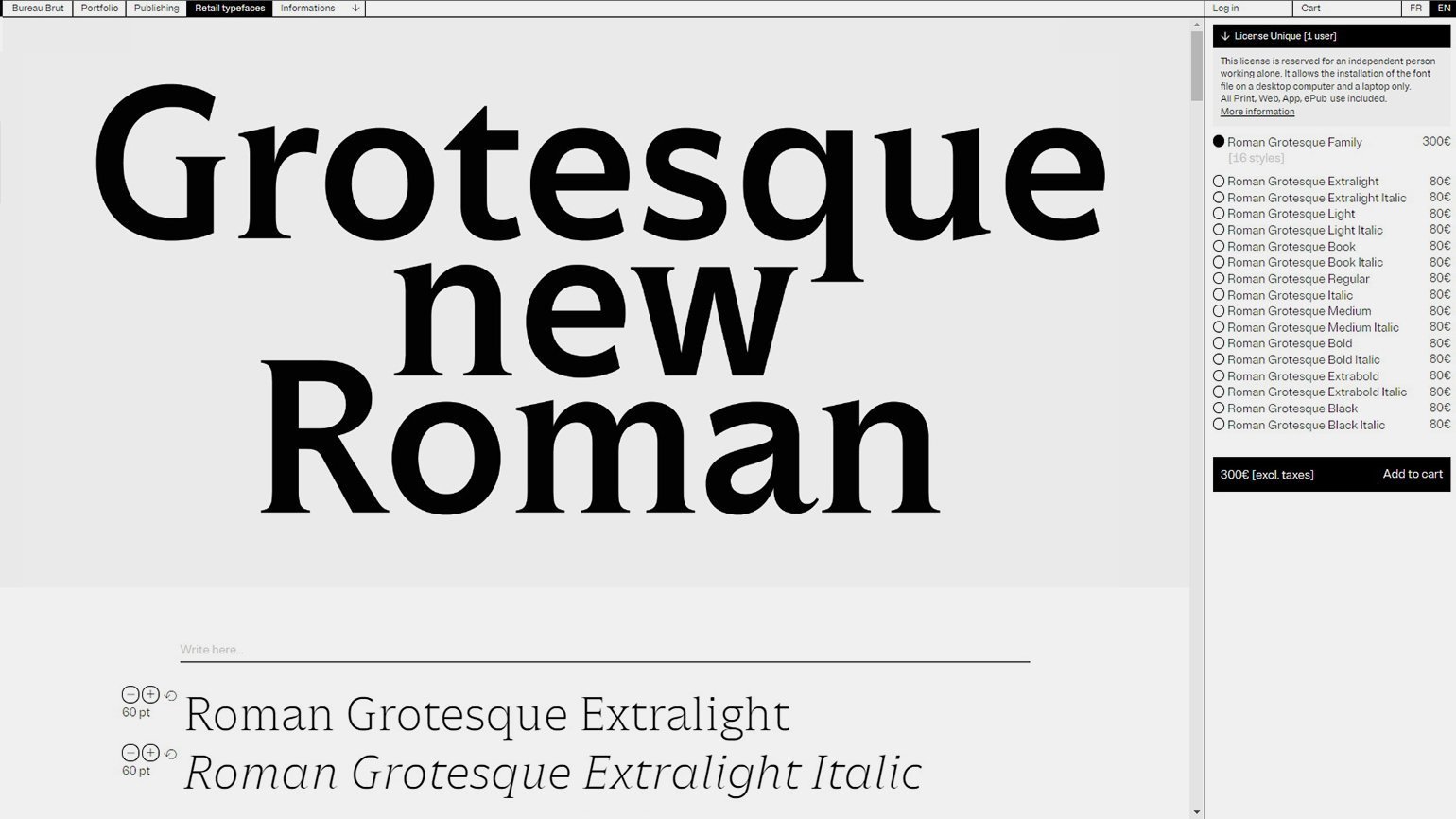
Неоднозначные термины: что такое брендбук, логотип и шрифт на самом деле
Надкусанное яблочко Apple — это не логотип, а заказчик просит сделать ему вовсе не брендбук. Рассказываем о путанице в терминологии.
Разночтения и неправильное использование терминов — проблема, которая встречается во многих сферах, и профессионального сленга графических дизайнеров она тоже касается.
Разберёмся, что на самом деле значат широко используемые термины и почему знать их настоящий смысл нужно, а вот правильно говорить — необязательно.
Брендбук и гайдлайн
Брендбук — это пособие для всех сотрудников, документ с изложением концепции бренда. В брендбуке описывают:
• философию компании;
• ценности корпоративной культуры;
• целевую аудиторию;
• конкурентные преимущества продуктов;
• а также — правила использования визуального фирменного стиля.
Для детального руководства по фирменному стилю есть отдельное название — гайдлайн.
В гайдлайне описание бренда и его мифов ограничивается несколькими абзацами, и эта информация в нём используется только для обоснования визуальных решений. А вот нюансы применения каждого элемента айдентики расписаны во всех подробностях.
Гайдлайн адресован не всем сотрудникам, а только маркетологам и дизайнерам, которые будут работать над рекламными кампаниями и поддержанием фирменного стиля компании.
Этот брендбук Skittles — инструмент бизнеса: он учит и вдохновляет сотрудников
Гайдлайн — это в первую очередь технический документ
Пример содержания гайдлайна: в нём прописаны используемые цвета, шрифты, допустимые версии фирменного знака, дизайн брендированной продукции
В обиходе и владельцы бизнеса, и дизайнеры зачастую называют гайдлайн брендбуком. Это привычно для всех, хотя формально неправильно.
Потребности в «настоящем», объёмном брендбуке у большинства компаний нет: «книги брендов» создают в крупных корпорациях с долгой историей и сложной системой маркетинга. А у небольших фирм характеристика бренда умещается в несколько предложений — и такого описания для гайдлайна достаточно.
Логотип и фирменный блок
Термин «логотип» образован от греческого «логос» — «слово». Правильное значение этого понятия — название компании, написанное именно буквами и определённым образом.
Слово martina — логотип, в котором шрифт сочетается со стилизованным изображением буквы «а»
Если же есть ещё и нарисованный символ бренда, эту картинку правильно называть фирменным знаком.
Изображение головы с лучами — фирменный знак, по которому бизнес можно узнать и без подписи
У Google, IKEA и многих других компаний нет рисунка-символа, а есть только название, написанное определённым образом.
Обычно фирменный знак и логотип используют вместе, и такое сочетание называется фирменным блоком.
Иногда в фирменный блок может входить слоган компании или лаконичное описание её профиля.
На лейбле фирменный блок: и легко узнаваемая картинка, и имя бренда
Дизайнерам редко заказывают разработку логотипа или создание символа бренда по отдельности. В большинстве случаев клиенту нужен именно фирменный блок — хотя и называют его по ошибке логотипом.
Если же требуется сделать логотип в строгом смысле этого слова, его называют шрифтовым или типографическим логотипом. Лексически это избыточно, но удобно и уже привычно.
То, что ошибочно называют шрифтовым логотипом. Это просто логотип в прямом смысле слова — с использованием леттеринга или шрифта
Изображение: Елена Клецкина / Behance
Шрифт и гарнитура
Шрифт — это набор символов в определённом стиле с единым начертанием.
Но есть ещё шрифтовая гарнитура — семейство шрифтов, в которое входят наборы символов, объединённые общей логикой построения и визуальными характеристиками.
Например, Helvetica — это гарнитура. В неё входят прямые и наклонные, толстые и тонкие буквы, но у всех сходные контрасты линий, пропорции и изгибы штрихов. А вот Helvetica Bold Italic — это уже конкретный шрифт: жирный и наклонный.
В некоторых гарнитурах вариантов шрифтов два или три, а иногда — десятки.
Roman Grotesque Extralight — шрифт. Roman Grotesque Book — тоже шрифт
Скриншот: сайт Bureau Brut / Skillbox Media
Каждый дизайнер точно знает разницу между шрифтом и гарнитурой, но в повседневной речи большинство не соблюдают точную терминологию. А люди, далёкие от дизайна, о гарнитурах могли даже не слышать.
На бытовом уровне в разделении шрифтов и гарнитур нет острой потребности. Обычно если просят напечатать название «шрифтом» Bodoni, то имеют в виду Bodoni Regular. А если нужно не Regular, тогда уж уточняют: Bodoni Light, Bodoni Bold или Bodoni Italic.
Если знать, что даже подобные простые слова люди могут понимать по-разному, это поможет избежать проблем с трактовкой и, как следствие, с работой над проектом.